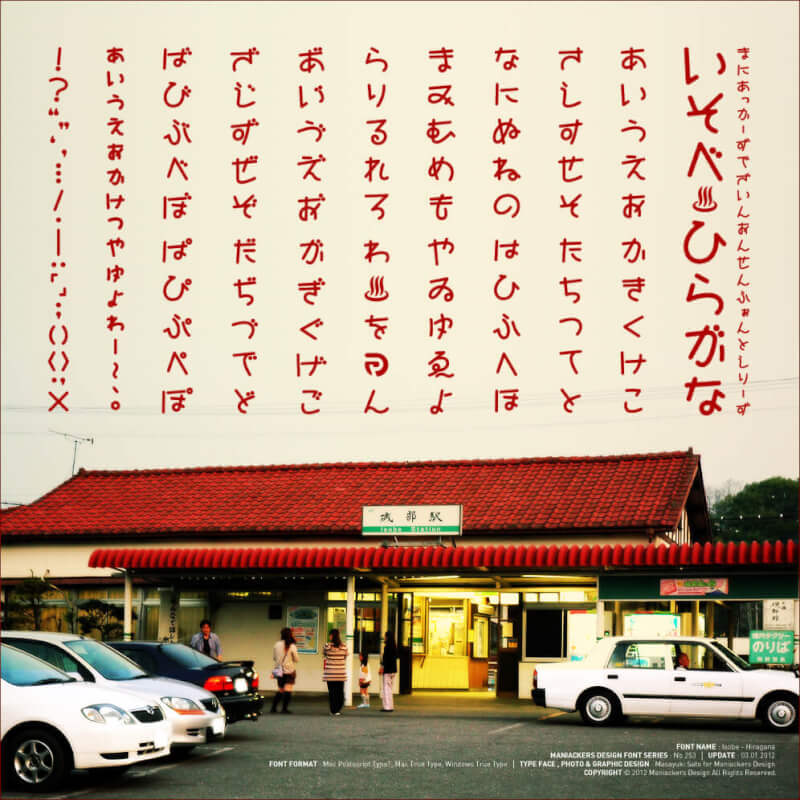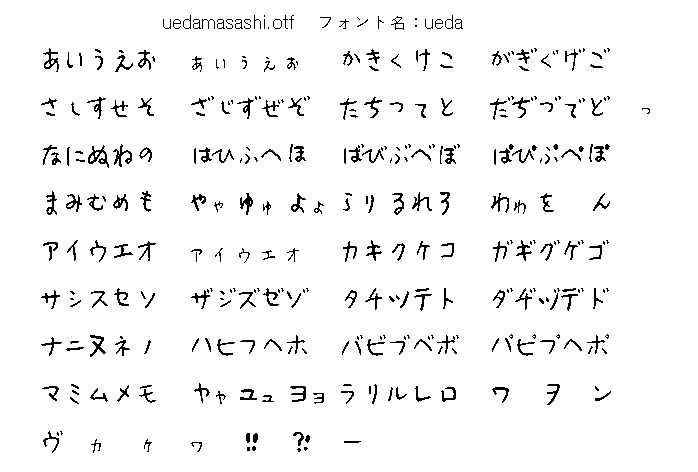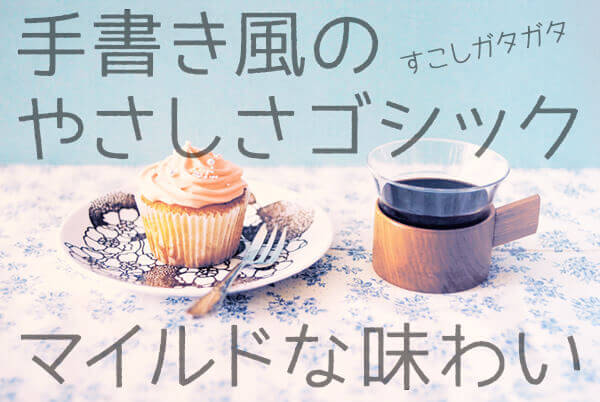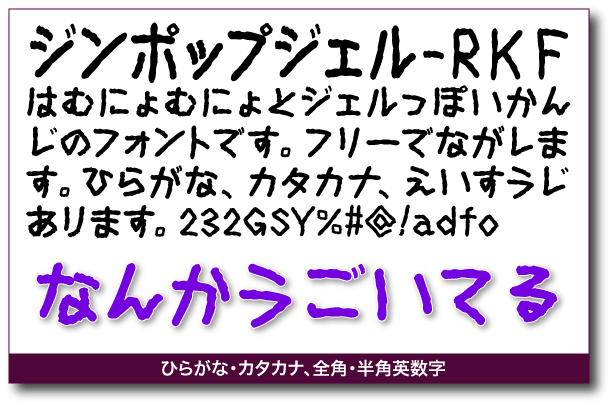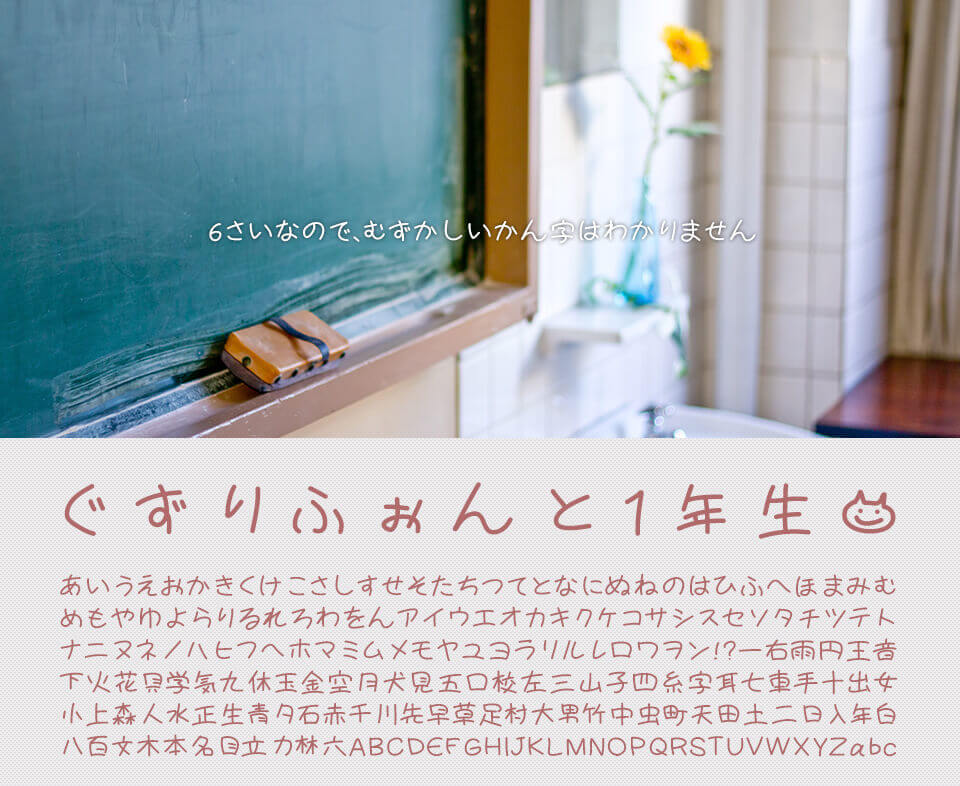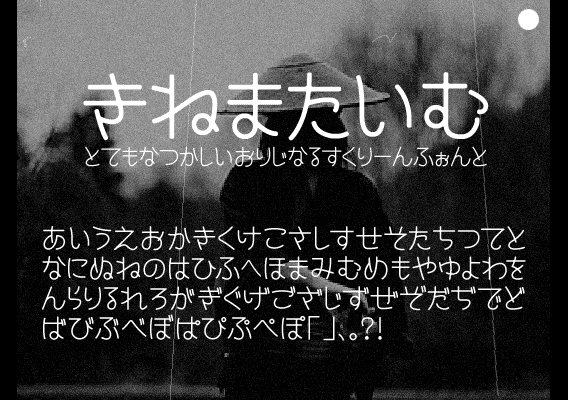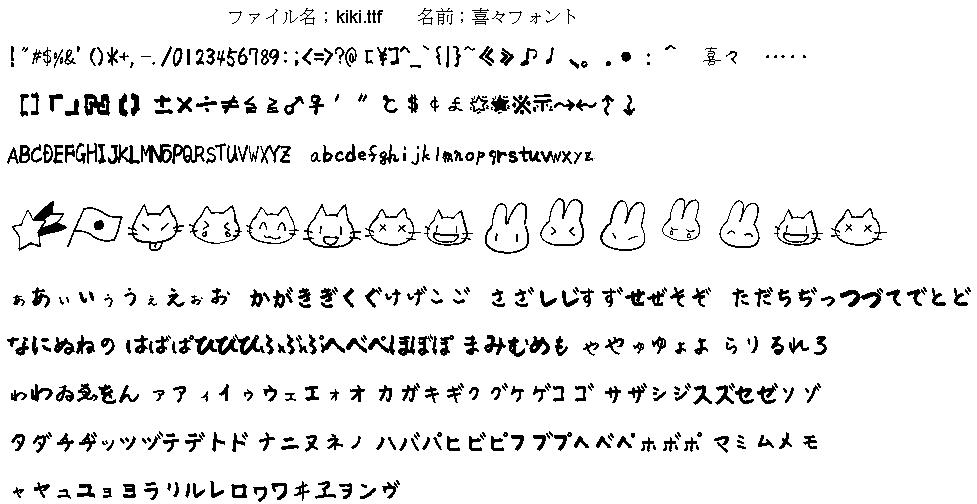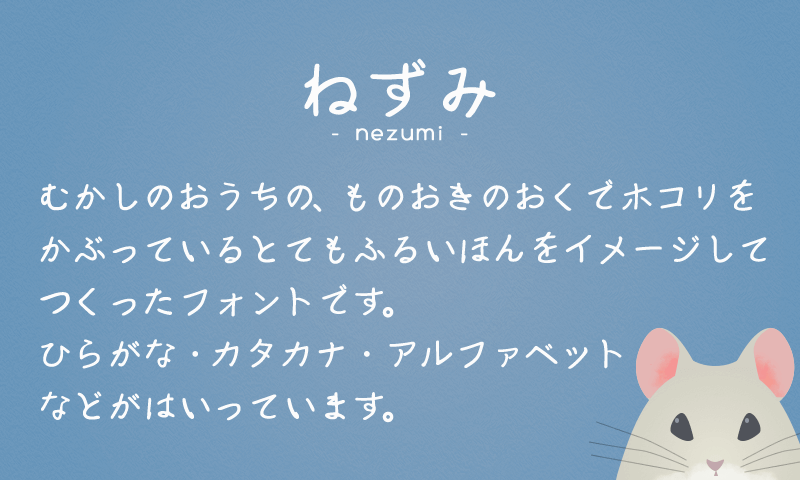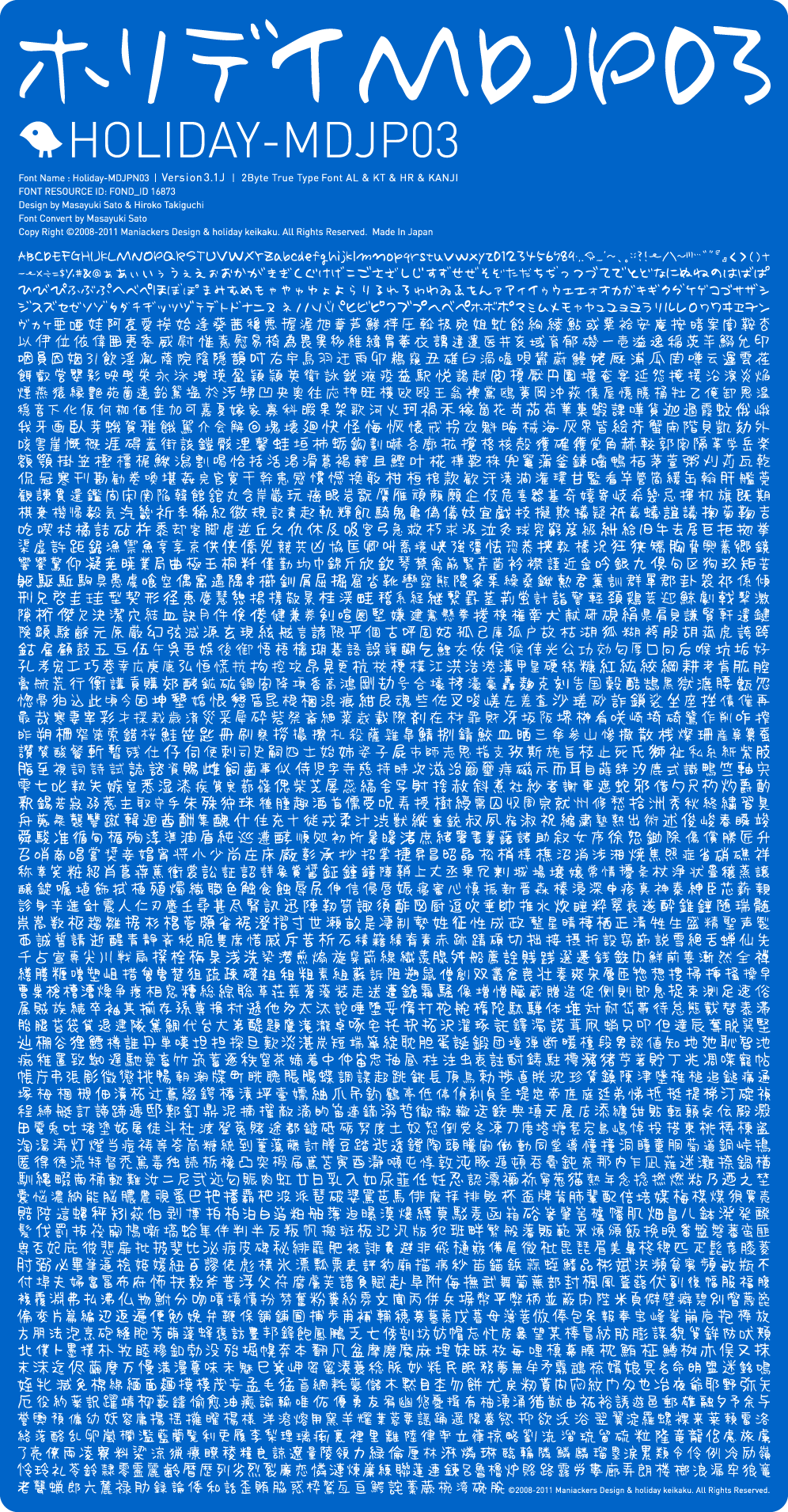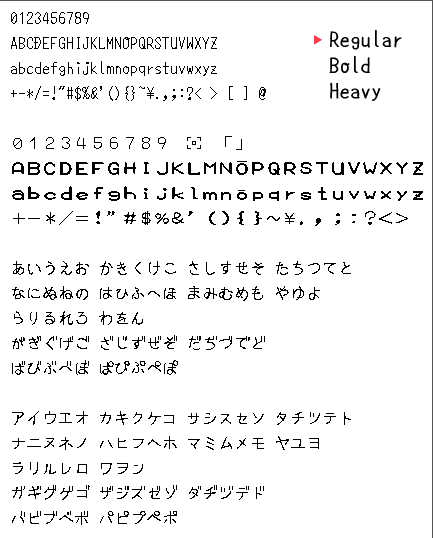
無料でダウンロード!手書き風の日本語フリーフォント66個
無料で利用できる手書き風(てがきふう)フォントを集めてみました。フォントをダウンロードすればテキストを入力するだけで手書き風文字を表現することができます。これからの季節だと年賀状を書くのに活躍しそうです。手書きでありながら漢字も多く収録しているフォントもあります。ぜひお気に入りのフォントを見つけてみましょう!
#6F9FF0
フォント名の通り青色(#6f9ff0)をイメージした英数字フォント。
Childish-AL, KT, HR
デジタルっぽい斜めに傾いたフォント。Nintendo DS新発売の際、CMで使用されたフォントだそうです。
MTたれ
落書き調のユニークなプロポーショナルフォント。
MTたれっぴ
落書き調のユニークなプロポーショナルフォント。漢字は第1水準漢字、第2水準漢字のすべてを収録。文字幅が文字によって異なる。
No.023
手書き風のフリーのカナフォント。
No.024
手書き風のフリーのカナフォント。
No.025
手書き風のフリーのカナフォント。
S2GPうにフォント
手書き文字から作成されたフォント。プロポーショナルフォント。
S2GPつきフォント
手書き文字から作成されたフォント。プロポーショナルフォント。
S2GP殴り書き
手書き文字から作成されたフォント。プロポーショナルフォント。
S2GP海フォント
手書き文字から作成されたフォント。プロポーショナルフォント。
S2GP月フォント
手書き文字から作成されたフォント。プロポーショナルフォント。
S2Gうにフォント
手書き文字から作成されたフォント。等幅フォント。
S2Gつきフォント
手書き文字から作成されたフォント。細めで可愛いい等幅フォント。
S2G殴り書き
手書き文字から作成されたフォント。等幅フォント。
S2G海フォント
手書き文字から作成されたフォント。等幅フォント。